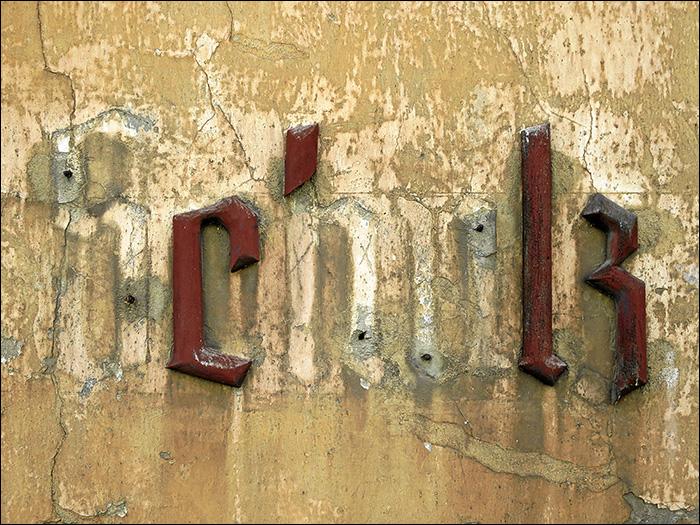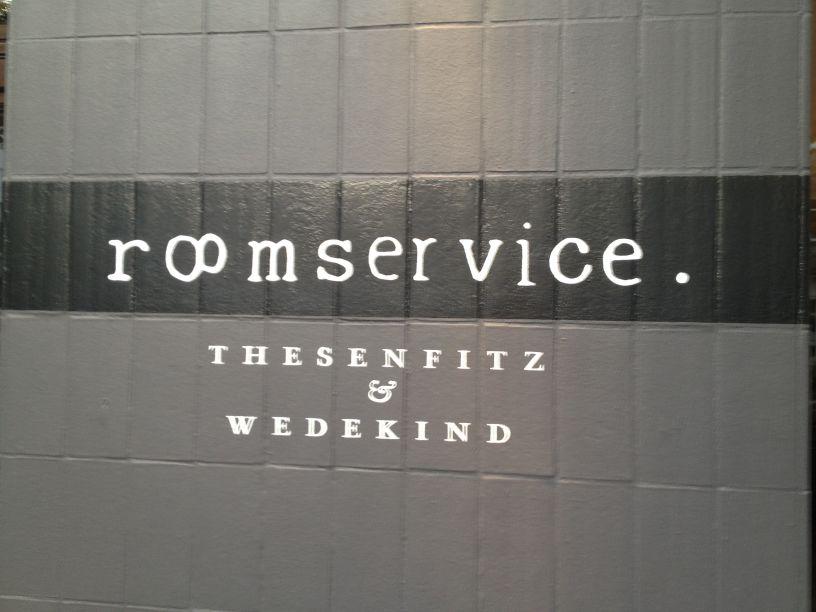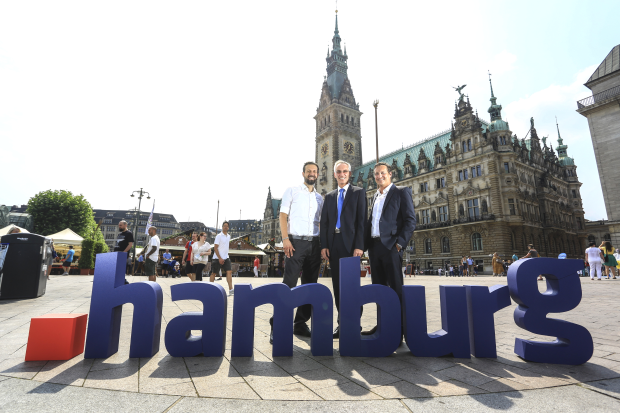
Leider finde ich Kathrins lustigen Thread, in dem sie einige typographische Details ihres Arbeitsweges dokumentierte, nicht wieder, aber hier ist das genauso gut aufgehoben :)
"Ligatur" im Lehmweg:
Immer diese störenden Unterlängen!
(Vorstellung der neuen Domain-Endung ».hamburg« in Hamburg,
gefunden auf Abendblatt.de)
Oder man hätte zum U-Bahn-Eingang gehen sollen -. oder auch der anderen Seite dees Rathausmarktes, und das g eine Stufe tiefer stellen sollen
Klar: der OB – der Oberste Buchstabenhalter. Sollte schließlich jede Metropole in der Verwaltung vorrätig haben …  :nicken:
Nur der gemeine. Der oberste trägt das Kürzel OB. Man muss sich ja schließlich vom Fußvolk abheben …
Du meinst doch sicher den Obersten Buchstabenhalter, der auch schon auf den Fluchhafen BER das "Berliner ß" in der Hausschrift präsentieren durfte?
... oder mit .hamburch ;-)